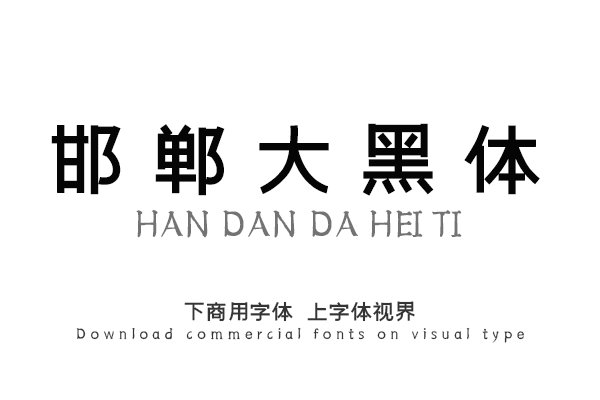
邯郸字库从最初发布的千字文到后来的各种创意字体,在字体视界平台已经有了一定的关注度和粉丝量。为了感恩回馈广大喜欢邯郸字库的用户,近期邯郸字库在字体视界上架了新的商用字体——《邯郸大黑体》。接下来跟随小字的脚步一起来欣赏一下这款不一样的美黑字体!
邯郸大黑体这款字体是以韩绍杰老师书写的美术黑体字为原型创作而成,笔画的粗细一致,中宫比较紧凑。黑字面大,字型朴素清秀,结构严谨,黑白均匀,重心一致;笔划制作精良,线条刚柔相济,简洁有力。